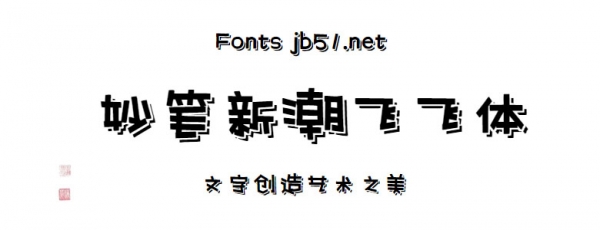
字魂妙筆新潮飛飛體是由字魂字庫推出的裝飾藝術(shù)字體,這款字體筆觸適中,字形圓潤(rùn),具有很好的視覺感,適合應(yīng)用于藝術(shù)設(shè)計(jì)、平面宣傳設(shè)計(jì)、網(wǎng)頁設(shè)計(jì),書法字帖等領(lǐng)域。
妙筆新潮飛飛體字體是一款可商用的裝飾字體,該字體包含6763個(gè)中文、字母、 符號(hào)和數(shù)字,具有時(shí)尚的風(fēng)格,可以滿足您設(shè)計(jì)上的各種需求,該字體主要用于標(biāo)題等場(chǎng)景, 您不但可以在字魂網(wǎng)下載妙筆新潮飛飛體字體,同時(shí)還有眾多毛筆書法字體、創(chuàng)意字體等可供選擇!